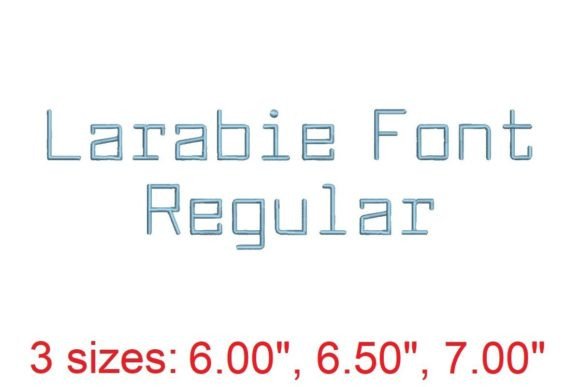
Larabie Font LT Embroidery Font
Encontrar los elementos de diseño adecuados puede ser un desafío, pero Larabie Font LT Embroidery Font ofrece una colección excepcional que eleva tu trabajo al instante.
Elaborado con precisión, Larabie Font LT Embroidery Font proporciona vectores limpios, tipografía suave y una licencia comercial para tu tranquilidad.
Ya sea que estés creando productos POD (impresión bajo demanda), invitaciones de boda o gráficos para redes sociales, Larabie Font LT Embroidery Font es una opción ideal.